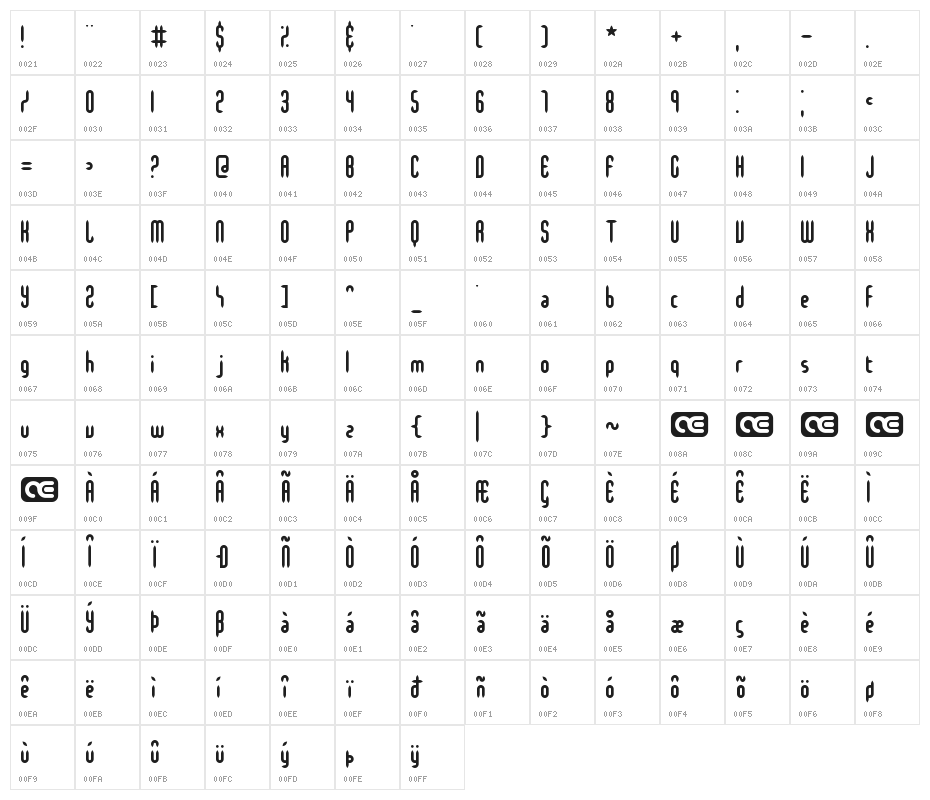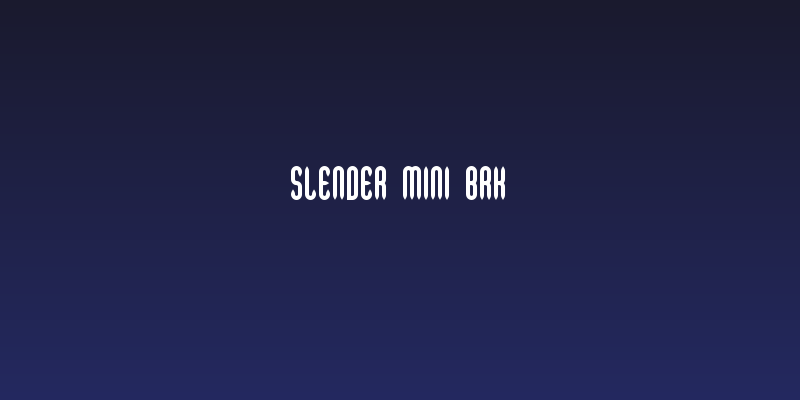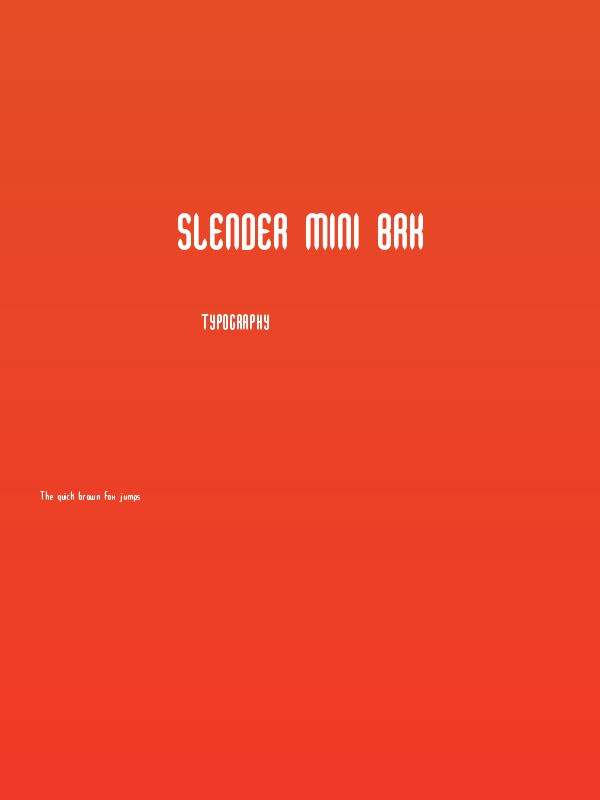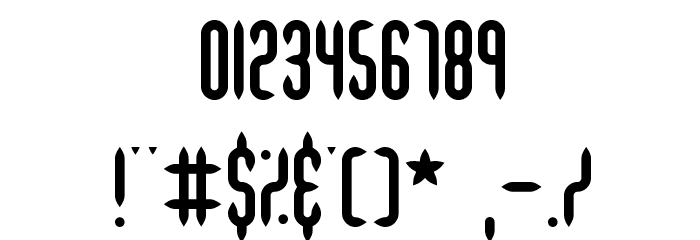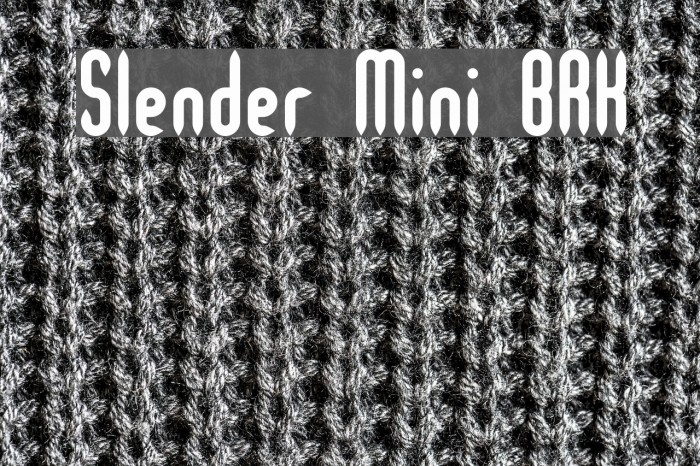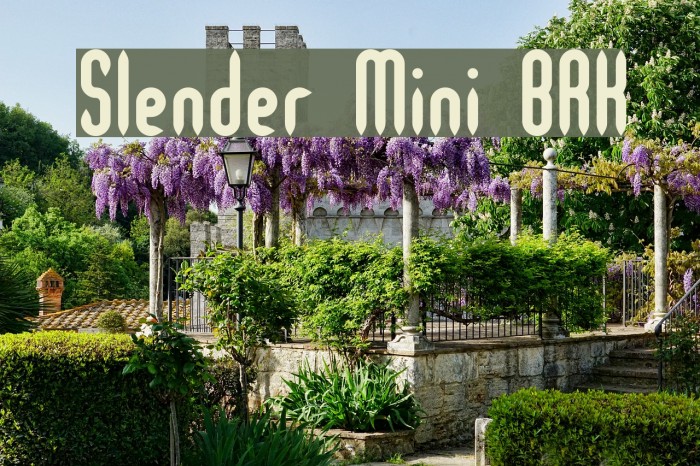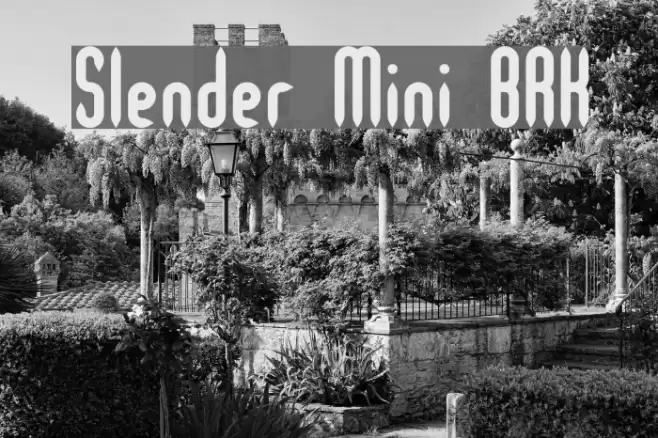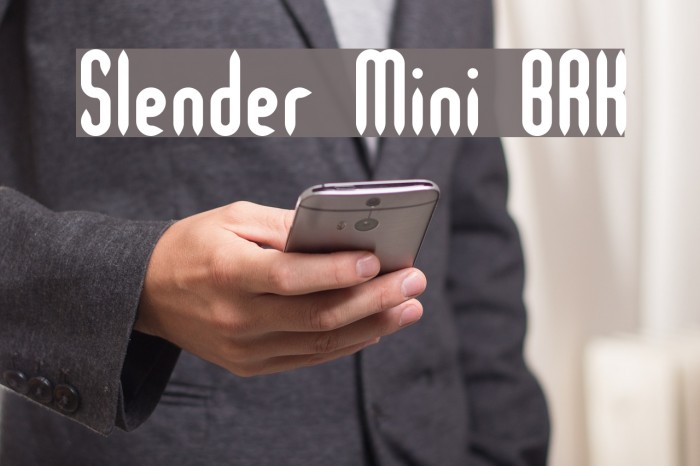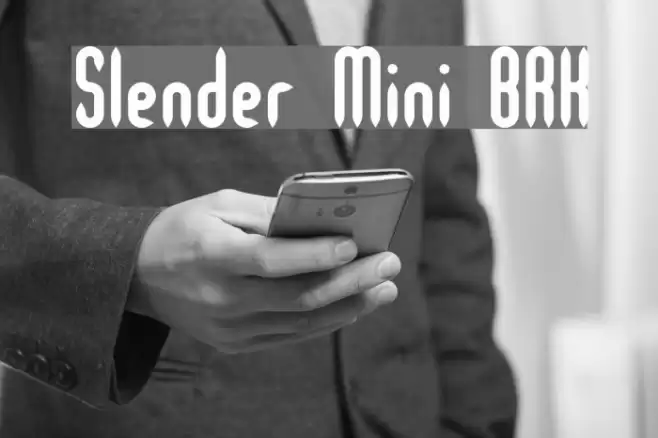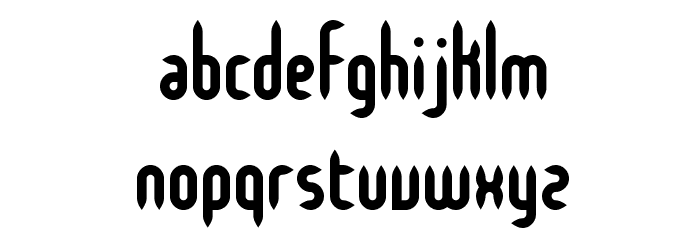
Slender Mini BRK Font
| Projets proposés | Ideal for creative projects such as posters, branding, and packaging design where a modern and playful touch is desired. |